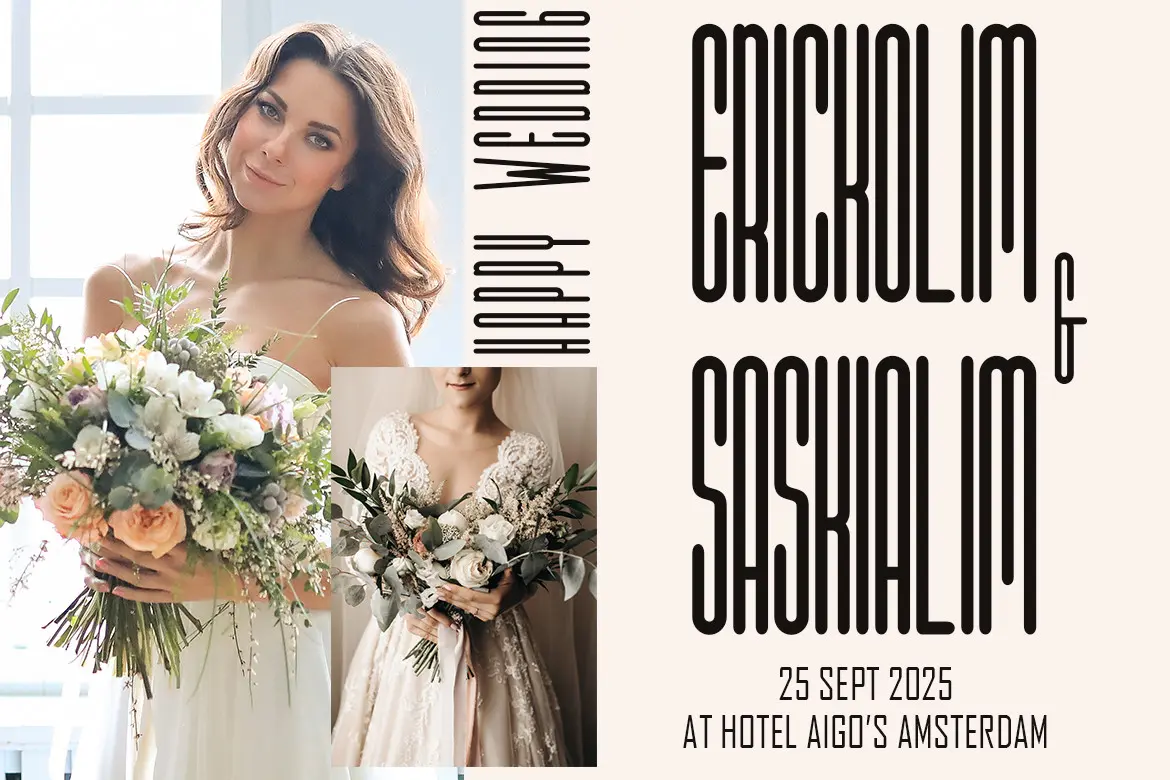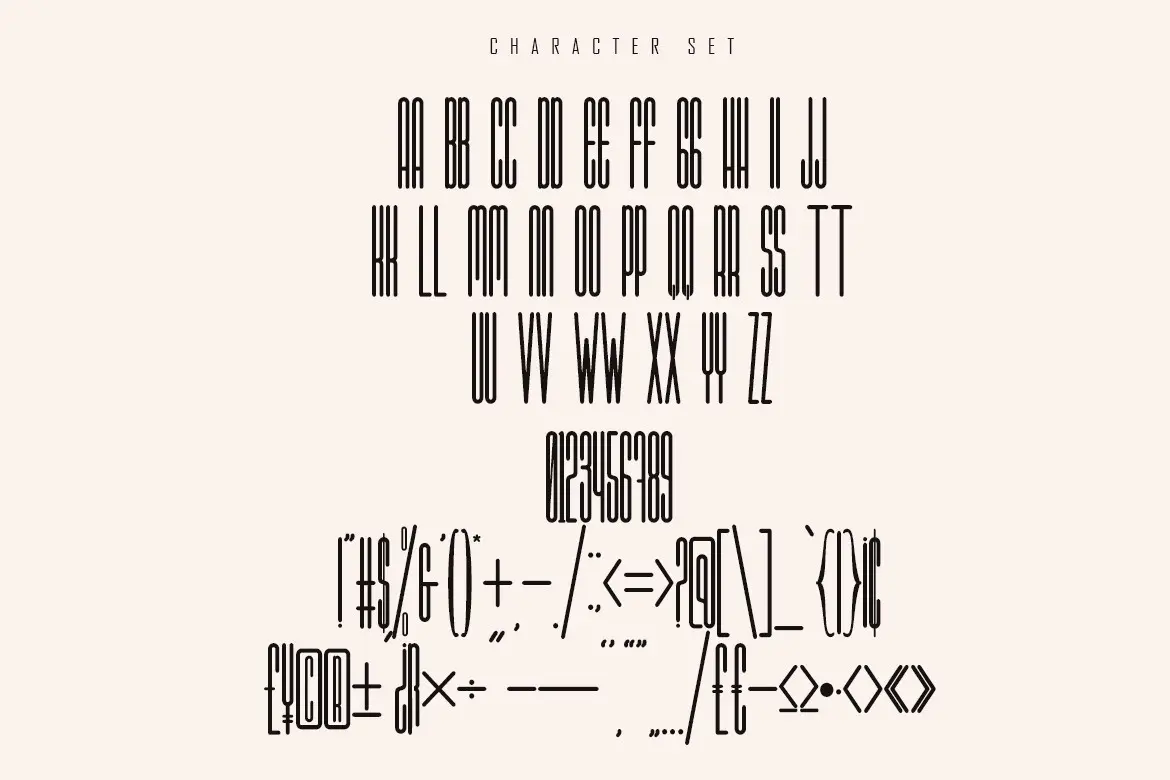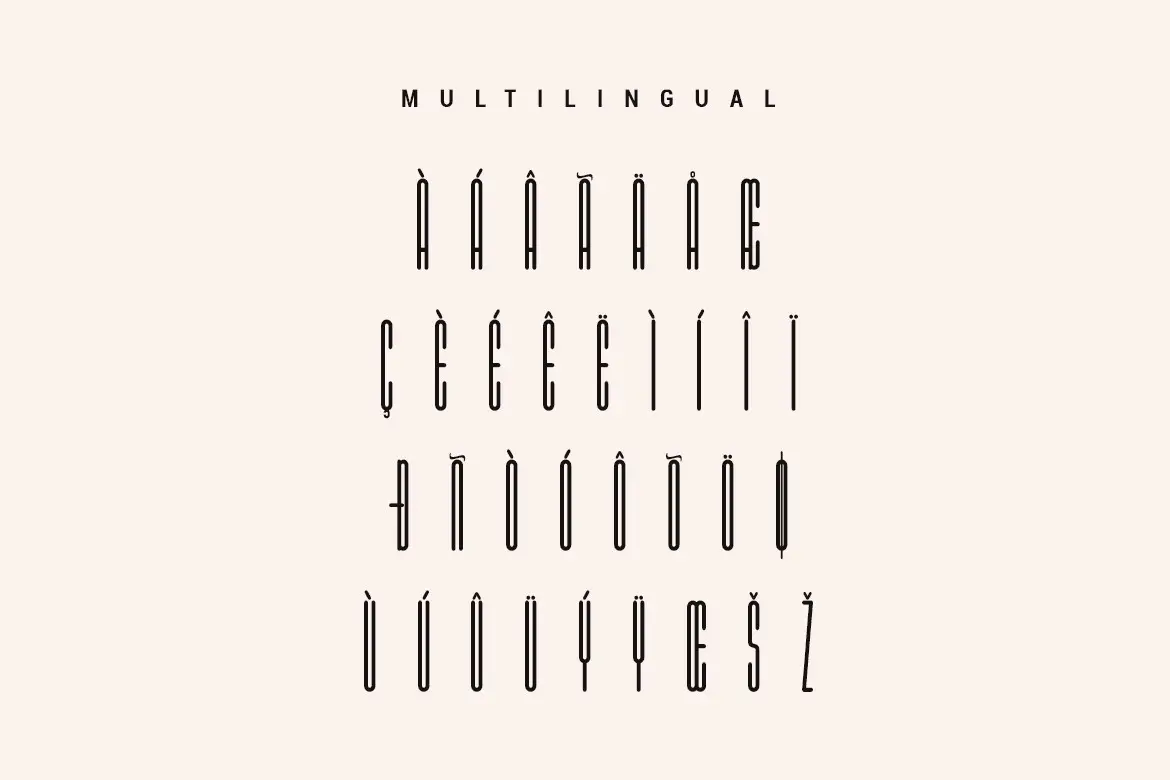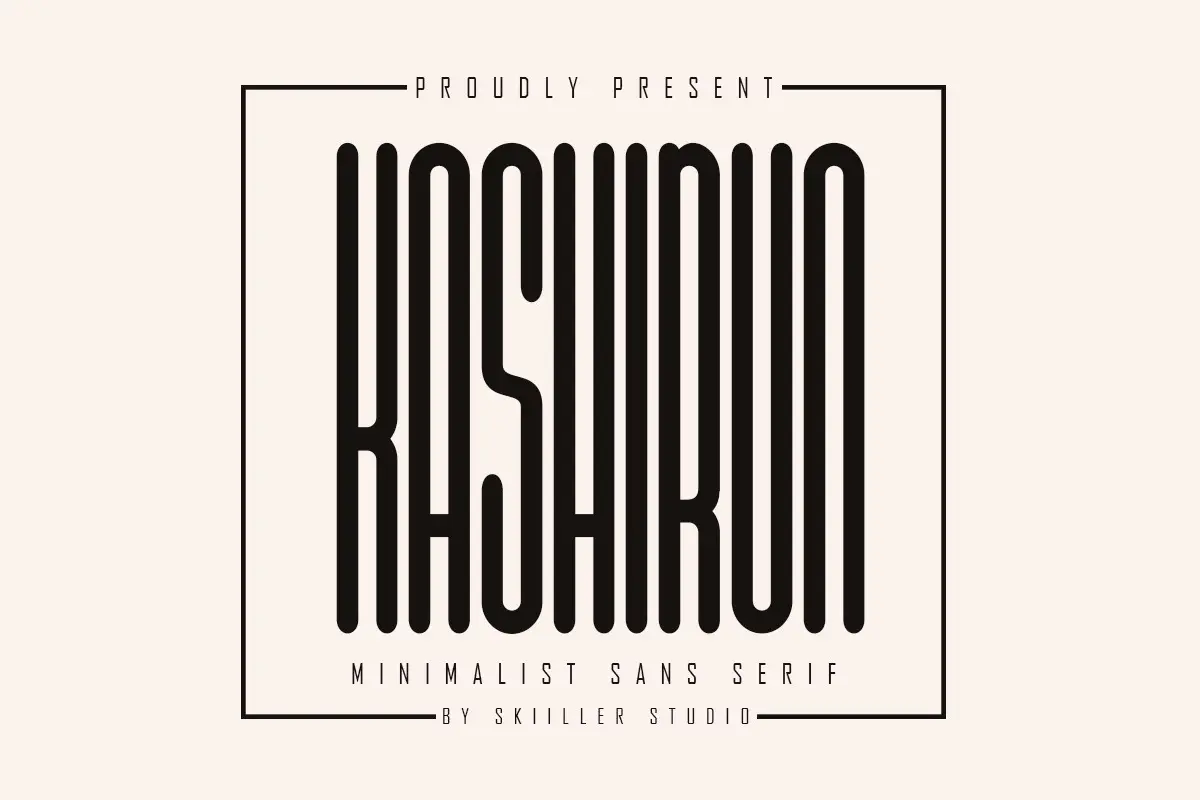
فونت مدرن و مینیمالیست
Kashirun یک فونت سنسریف فشرده (Condensed Sans Serif) با ظاهری مدرن، شیک و مینیمال است که به طراحیهای شما حس حرفهای و الهامبخش میدهد. این فونت با فرم باریک و جمعوجور خود، برای پروژههایی که نیاز به تایپوگرافی تمیز، امروزی و چشمگیر دارند انتخابی فوقالعاده است.
⭐ ویژگیها
- سبک Condensed Sans Serif
- ظاهر الگانس، کلاسیک و مدرن
- مناسب برای انواع طراحیها از جمله:
- لوگو
- پوستر
- برندینگ سازمانی
- لیبل و بستهبندی
- تیتر و تایپوگرافی تبلیغاتی
- الهامبخش و قابل استفاده در پروژههای خلاقانه